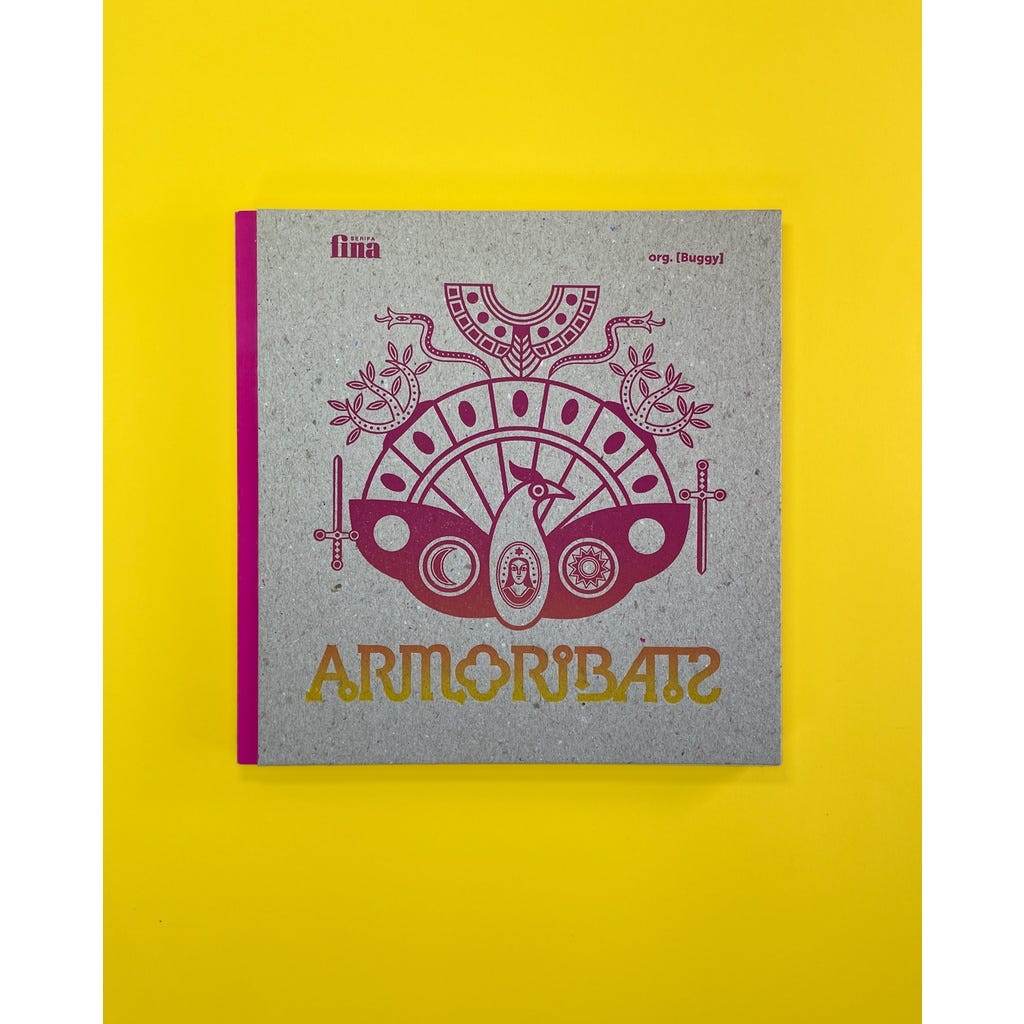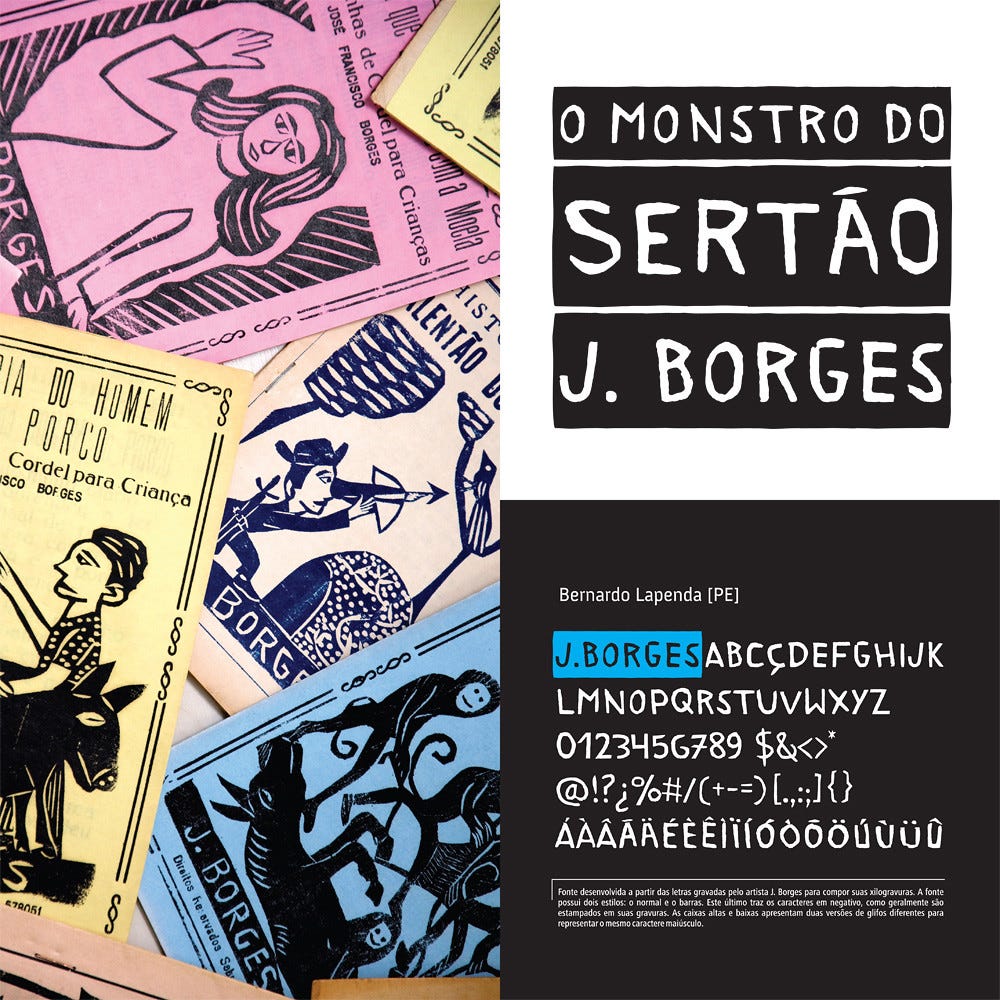
Tipo Aquilo #57 – Ariano, Borges, Samico e Armoribats
Um olhar tipográfico sobre o Movimento Armorial
Viver com uma pernambucana me garante uma quantidade periódica de risadas (respeitosas) sobre a grandiosidade de tudo que vem do estado e suas maiores cidades. Ninguém que conversa com um pernambucano passa incólume pela história da avenida em linha reta mais longa da América Latina ou pelo maior bloco de carnaval de rua do Brasil. Essa coisa arraigada, com ares de fantástica e mágica, tem raízes profundas: a antiga capitania de Pernambuco já foi a mais rica do Brasil, pertenceu a outro reino por um breve tempo, foi até um país independente e permaneceu como um grande polo de produção artística e cultural até hoje. Se isso não é uma história incrível de se contar, não sei o que mais pode ser.
Na década de 1970, um grupo de artistas e pensadores também tinha isso em mente; a cultura sertaneja, que parecia perdida e largada no interior, tinha uma identidade tão única e marcante que valia a pena ser revista com um novo olhar, com a intenção de fazer dela uma arte erudita, bem quista pelas pessoas, que fizesse frente à cultura estrangeira que parecia dominar o país. Esse afã de colocar no palco as manifestações populares e a tradição local, transformando-os em objetos de admiração, motivou o nascimento de um dos mais importantes movimentos culturais da história do Brasil. Encabeçado por Ariano Suassuna, nem o futuro esperava pelo que viria com o Movimento Armorial.
É fato que Suassuna é bastante conhecido Brasil afora graças às dezenas de reprises do filme “O Auto da Compadecida” de Guel Arraes (não tô reclamando não, Globo, reprisa a minissérie também, e já emenda “A Pedra do Reino” em seguida). O intelectual paraibano foi autor de várias obras igualmente fantásticas, como o Romance d’A Pedra do Reino e o Príncipe do Sangue do Vai-e-Volta e O Santo e a Porca (também presente na adaptação de Arraes), mas falar de Ariano apenas como dramaturgo é um pecado. Muito das referências visuais que temos do Nordeste deve-se ao Movimento Armorial, uma iniciativa de Ariano dedicada a enaltecer a cultura do agreste, criando uma arte erudita em torno das histórias, do folclore e do modo de viver da população sertaneja. “Uma Arte brasileira erudita a partir das raízes populares da nossa Cultura”, nas palavras de seu próprio idealizador.
Como tudo que permanece, o Movimento Armorial não veio do nada; intelectuais como Gilberto Freyre, em seu Manifesto Regionalista de 1926, já propunham a necessidade de resgatar a riqueza cultural do agreste e conciliá-la com a cultura europeia, tida como ideal de erudição desde a colonização do Brasil e preferida pelos meios de comunicação em massa. O manifesto de Freyre somava-se a outras iniciativas de resgate da cultura brasileira sob o guarda-chuva do modernismo da década de 1920. Ariano, por sua vez, tinha a experiência de trabalho com o Gráfico Amador, que buscava na cultura pernambucana as referências gráficas para seus experimentos (tipo)gráficos, e proporcionou contato frequente com pessoas do gabarito de João Cabral de Melo Neto e Aloísio Magalhães.
Ariano também conhecia a distância além do mero espaço físico que separava o nordeste litorâneo do nordeste interiorano, onde tiveram refúgio o mamulengo, maracatu, reisado e outras manifestações populares resgatadas pelo Armorial. Os elementos marcantes, como as bandeiras, estandartes, os seres fantásticos vindos de uma mistura de histórias cristãs, indígenas e africanas, as cores primárias e vibrantes, o sol inclemente e a chuva redentora que marcavam o passar do tempo, animais e objetos do cotidiano, têm base num arcaísmo alimentado por essa distância que isolava a população sertaneja e mantinha relações sociais e políticas próximas às do feudalismo. Com o concerto “Três Séculos de Música Nordestina: do Barroco ao Armorial”, em 18 de outubro de 1970, e uma exposição de gravura, pintura e escultura, Suassuna inaugurava uma valorização dessa cultura popular que persiste até hoje.
Apesar de ter essa data marcada, a arte Armorial já vinha sendo pintada, modelada, tecida, cantada e gravada por artistas que comungavam desse sentimento de resgate cultural. São vários nomes que merecem destaque além do próprio Ariano com seus romances e peças teatrais, como o ceramista Francisco Brennand e sua esposa poeta Deborah Brennand, o Quinteto Armorial, o artista plástico Miguel dos Santos, o poeta Patativa do Assaré, entre outros ilustres. Para manter o foco na tipografia e design gráfico, essa edição dá destaque a dois expoentes do Armorial que são referências para a gravura brasileira: J. Borges e Gilvan Samico.
Começando por J. Borges, que se você tem amigos influentes (e/ou hipsters), já deve tê-los ouvido falar “eu tenho um J. Borges em casa”, com toda a pompa que a metonímia evoca. Patrimônio vivo de Pernambuco e autor de gravuras expostas em grandes galerias mundo afora, José Francisco Borges fez de tudo um pouco antes de perder a vergonha e enveredar para as artes, quando decidiu escrever cordel. Em 1964, aos 29 anos, lançou seu primeiro cordel, “O Encontro de Dois Vaqueiros no Sertão de Petrolina”, que vendeu milhares de exemplares e deu ânimo para que ele seguisse em frente. No entanto, para seu segundo cordel, Borges precisou fazer por conta própria as ilustrações, talhando uma igreja num pedaço de imburana e entintando a matriz da capa de “O Verdadeiro Aviso de Frei Damião Sobre os Castigos que Vêm”, lançado em 1965.
Borges escreveu outros cordeis, como “A Mulher que Botou o Diabo Numa Garrafa”, “A Chegada da Prostituta no Céu” e outros trezentos folhetins, mas foi justamente o trabalho de xilogravura que tornou-lhe ilustre. Suas gravuras ilustravam elementos do ideário local em seus livretos, como Lampião, vaqueiros, diabos, padres, a natureza e as festas de São João. Na década de 1970, passou a receber encomendas de versões ampliadas de suas gravuras, e posteriormente, passou a adicionar cores em seu processo de criação e impressão. As gravuras e cordeis de Borges chegaram então até Suassuna, que passa a apadrinhá-lo e considerá-lo “o maior gravador popular do Brasil”. Os elementos da vida sertaneja tornam-se cult em museus de todo o mundo, tendo aparecido em capas de livros de Eduardo Galeano e José Saramago. De forma humilde, Borges até hoje imprime em seu ateliê, em Bezerros, onde vive de sua obra.
A assinatura de suas obras na parte inferior, feita com um alfabeto próprio, tornou-se uma marca de J. Borges, herdada pelo filho gravador J. Miguel. Além de gravador, Borges também tem um pé na tipografia, tendo composto os textos de seus cordeis em uma máquina tipográfica que o acompanha até hoje. A renovação do parque gráfico das cidades maiores, marcada pela chegada das máquinas de linotipo e, posteriormente, as impressoras offset, empurrou várias impressoras antigas para o interior, onde ajudaram a formar pequenas gráficas locais e registrar a cultura interiorana. Apesar de ter largado a escola cedo, J. Borges tinha vocação para aprender coisas novas e se aperfeiçoar, sendo autodidata como escritor, impressor, e uma referência mundial para a xilogravura.
Gilvan Samico é outro ilustre expoente da xilogravura, reconhecido internacionalmente e exposto em diversas galerias. No entanto, a história de vida dele é quase oposta à de J. Borges; nascido em Recife, aprendeu pintura por conta própria e juntou-se a outros artistas locais na Sociedade de Arte Moderna de Recife, em 1948, onde ajuda a fomentar uma renovação da arte pernambucana. Depois, estuda gravura com suas maiores referências da época, Lívio Abramo e Oswaldo Goeldi, desenvolvendo um grande apuro técnico na confecção das matrizes e impressão das peças. Teve também a oportunidade de estudar na Europa e, mais tarde, lecionar gravura na UFPB.
Os caminhos de Samico e Ariano se cruzam em 1971, quando é feito o convite para que o gravador junte-se ao Movimento Armorial. Suas peças também ilustravam o ideário sertanejo, com elementos da natureza, da religião e do cotidiano, dotados de aspectos místicos e mágicos. Samico segue um caminho próprio como artista, inspirado na literatura de cordel, produzindo gravuras muito ricas e detalhadas e com uso preciso de cores vibrantes, presentes nas manifestações culturais populares do sertão. Ao contrário da rapidez de J. Borges, Samico dedica-se com o passar do tempo a produzir menos peças por mais tempo, a fim de refinar o manuseio da goiva e experimentar outras formas de cortes até achar uma textura ideal. Tanto apuro faz com que, no circuito artístico, ele seja considerado por vários críticos o maior xilogravurista do país.
Os caminhos do Armorial e da tipografia nunca deixaram de se cruzar; Suassuna, além de escritor, produzia iluminogravuras que representavam a poética de seu movimento e continham letras desenhadas pelo autor que tinham como origem os símbolos usados nos ferros de marcar gado, em que cada detalhe da composição tinha um significado especial. Essas letras inspiradas em marcação de animais, que Ariano chamava de “Alfabeto Sertanejo”, tornaram-se uma referência tipográfica importante para o movimento. O fascínio pelo ferro de marcar acompanhou-o a vida toda, chegando a usar o ferro dos Suassunas, herdado de seu pai, para assinar suas obras. Posteriormente, na década de 1990, quando comandava a Secretaria de Cultura de Pernambuco, Ariano foi supervisor de Ricardo Gouveia de Melo e Giovanna Caldas na produção de uma versão digital da Tipografia Armorial.
Além das letras de Ariano, o trabalho de levantamento iconográfico do prof. Leonardo Buggy deu origem ao registro em formato vetorial de vários elementos comuns na produção gráfica do Movimento Armorial. O trabalho teve como resultado dois conjuntos de 52 ícones consolidados em duas fontes dingbats, possibilitando o uso desses elementos em formato digital sem perda de informação; outro fruto desse trabalho foi o maravilhoso livro Armoribats (2022, Editora Serifa Fina), organizado por Buggy, que destrincha cada ícone com seu significado e importância para o movimento. No primeiro set, Buggy toma como influência a estética de cordel de J. Borges e as iluminuras de Suassuna; no segundo, o autor traz a perspectiva erudita de Samico e outros artistas plásticos.
O Armoribats é uma obra bem vinda, com acabamento impecável, e ideal para quem aprecia boa tipografia e/ou é fã do Movimento Armorial. Além dos dingbats feitos por Buggy, Gustavo Gusmão e Matheus Barbosa, também foi criada a Armordisplay, que revisita a Tipografia Armorial de Suassuna, simplificando seus traços, mas mantendo a essência da estética do ferro de marcar. Luciano Cardinali também explora o alfabeto sertanejo em sua fonte Nova Armorial. O cordel também é uma referência visual para outras fontes, como a Cordelia, de Erica Jung e Ricardo Marcin, e a Cordel, também de Buggy.
Entender o Armorial e seus artistas e pensadores ajuda a entender a imagem que o Brasil tem do Nordeste, e faz com que a região seja um foco de inspiração e admiração do país fora do eixo Rio-São Paulo. Se você pedir para um designer apontar uma referência visual dessa região, certamente ele falará do cordel, mesmo que o Armorial passe batido; só que o legado do Movimento Armorial vai além da produção artística. Ele está presente em toda vez que a gente olha para dentro e exalta o que a nossa cultura tem de única e especial, quando não se deixa que o belo venha apenas da grama do vizinho. Por mais discutível em certos aspectos que tenha sido a abordagem de Ariano, o Movimento Armorial tem uma importância inegável para a cultura brasileira; alguns dirão até que é a maior manifestação cultural nordestina em linha reta da América Latina. ;)
Para comprar:
🛒 Livro: Armoribats, organizado por Leonardo Buggy. Editora Serifa Fina.
Recomendações:
🎧 Podcast: Visual+Mente #178, com Leonardo Buggy, Almir Mirabeau e Ricardo Cunha Lima conversando sobre a produção do livro Armoribats.
🇧🇷 Fonte brazuca: J. Borges, de Bernardo Lapenda.